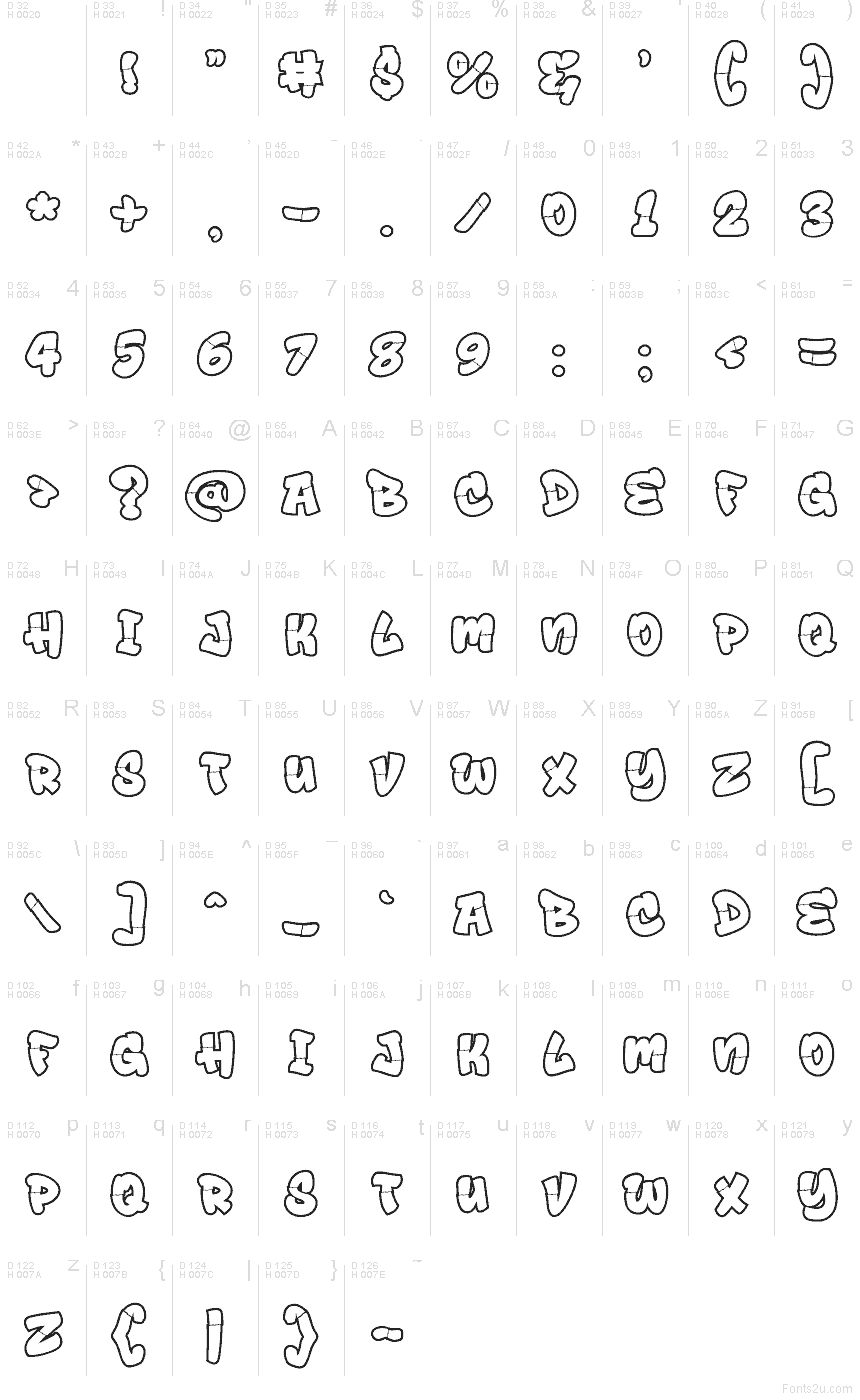
Il font Drop Shade Outlined Outline di Muhammad Panji Ramdhani (Sipanji x Cikareotype) cattura l'essenza del graffiti realizzato con il marker: forme gonfie, spazi interni ariosi e un contorno audace che sembra un adesivo appena applicato su un muro. Parte della famiglia Drop Shade Outlined, questo font graffiti gratuito mantiene un impatto visivo energico senza risultare confuso.
Drop Shade Outlined Outline è perfetto per loghi streetwear, poster di skate, miniature YouTube, copertine di album, volantini per eventi, set di adesivi e schermate di giochi. Impostalo con dimensioni generose per lasciare che il contorno respiri e abbinalo a un carattere sans serif condensato e pulito per i dettagli: questo font gratuito sa come farsi notare.